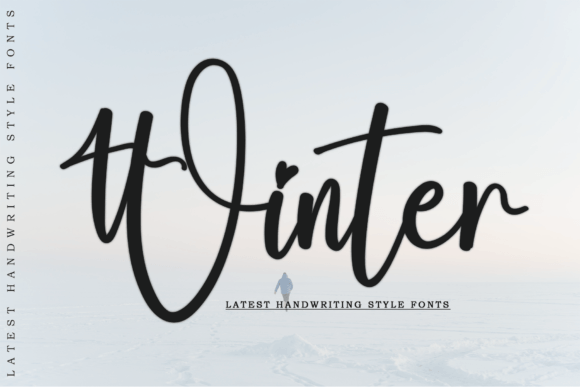
Winter
Trouver les bons éléments de conception peut être un défi, mais Winter propose une collection exceptionnelle qui rehausse instantanément votre travail.
Conçu avec précision, Winter offre des vecteurs nets, une typographie fluide et une licence commerciale pour une tranquillité d'esprit.
Que vous créiez des produits POD (impression à la demande), des invitations de mariage ou des visuels pour les réseaux sociaux, Winter est un choix idéal.